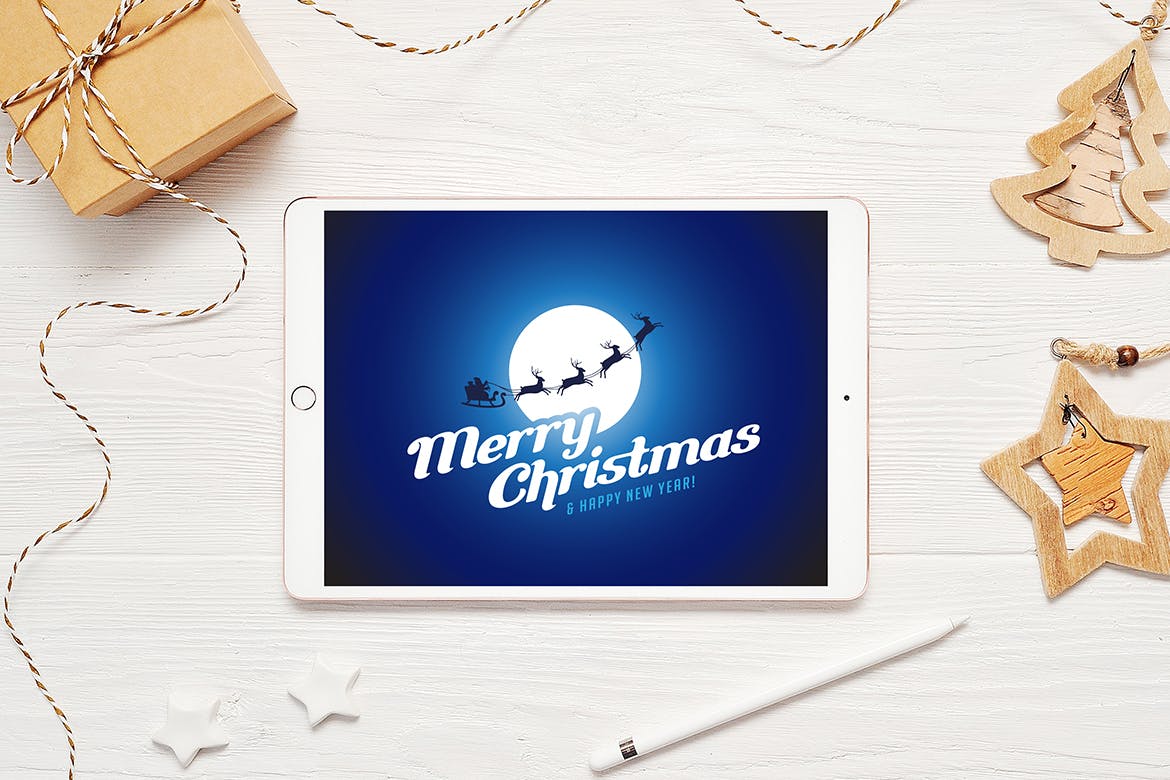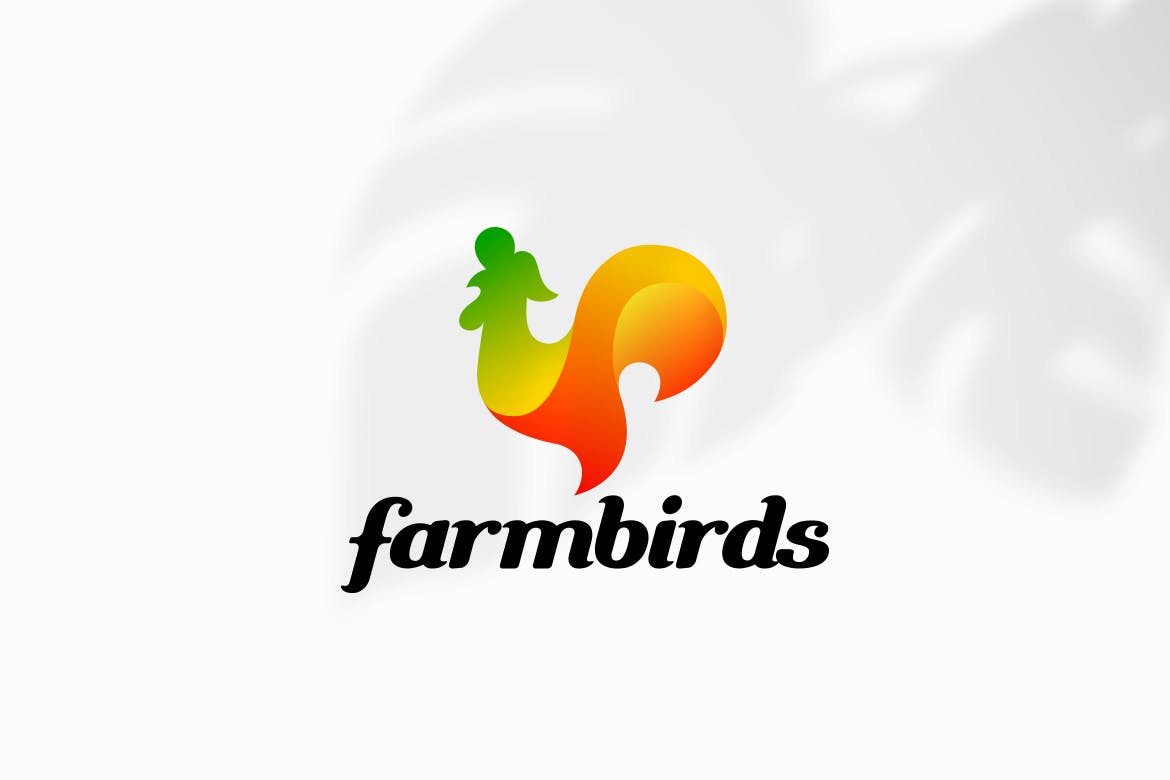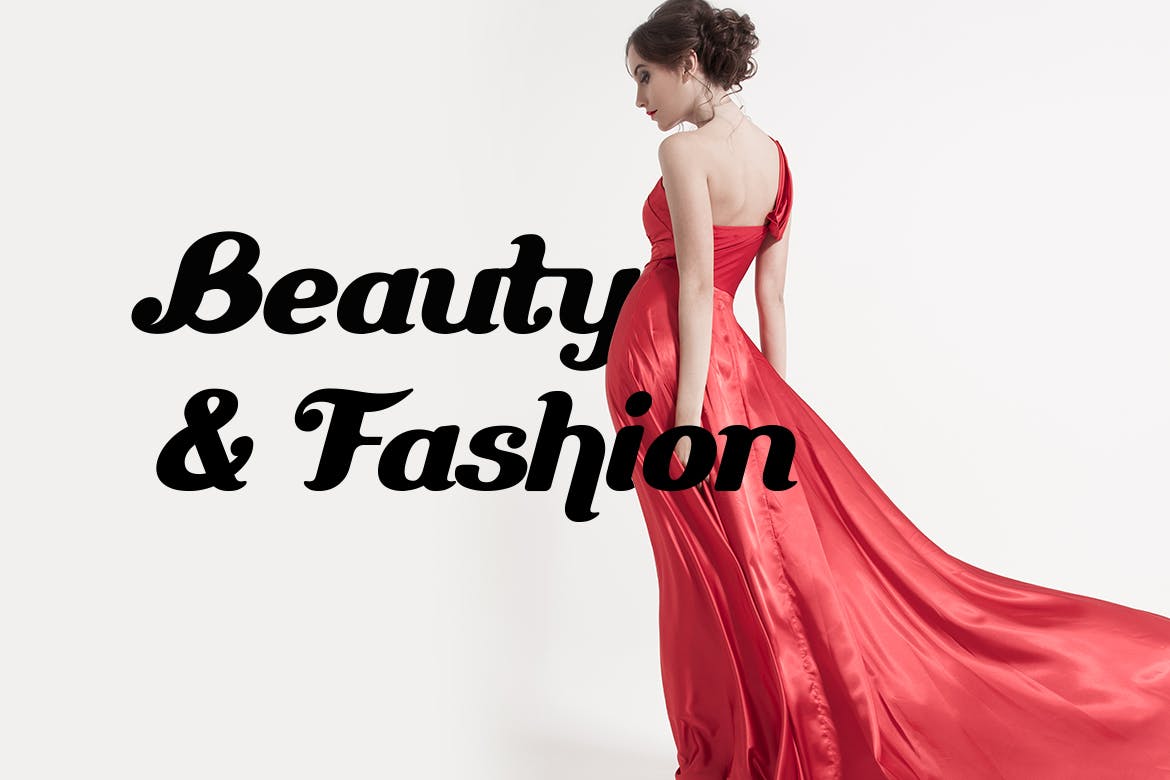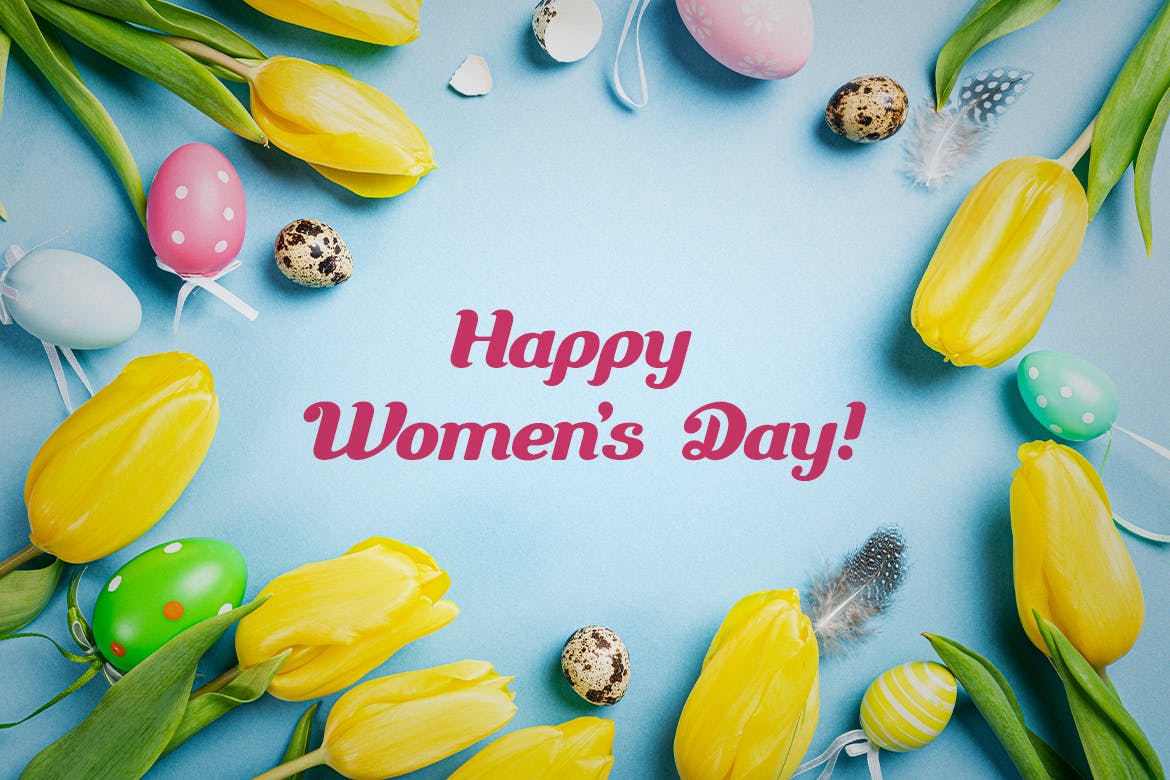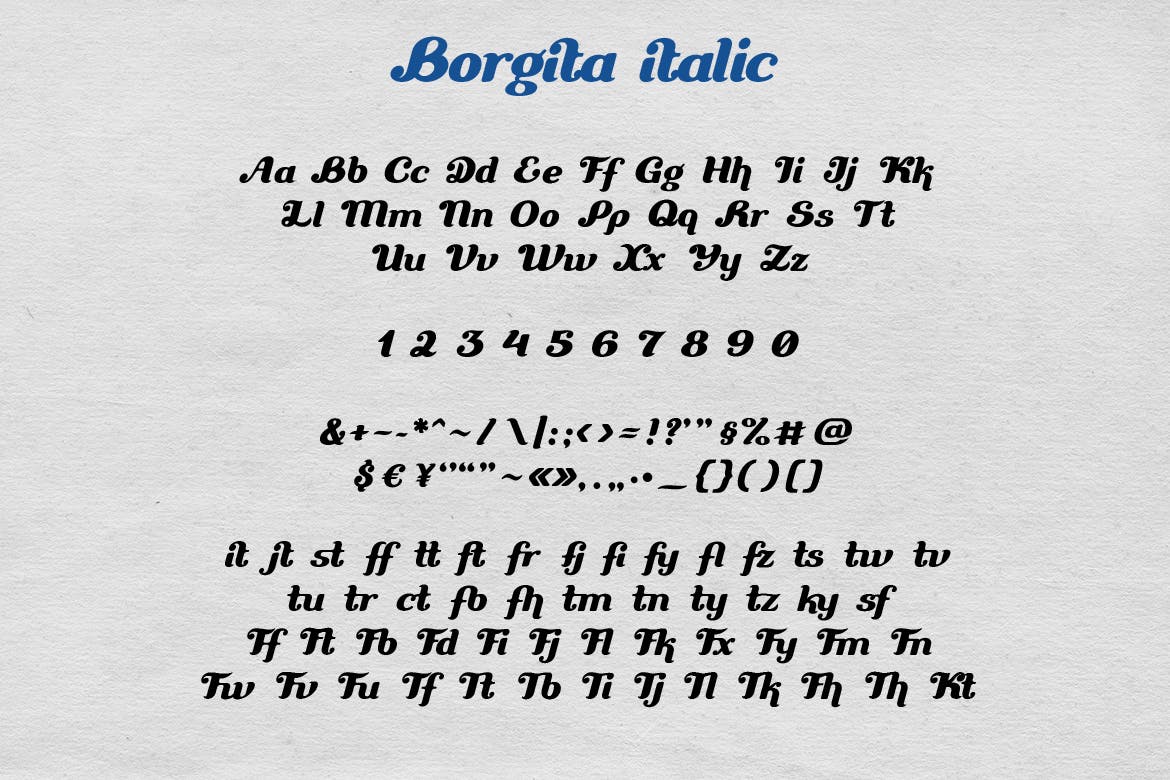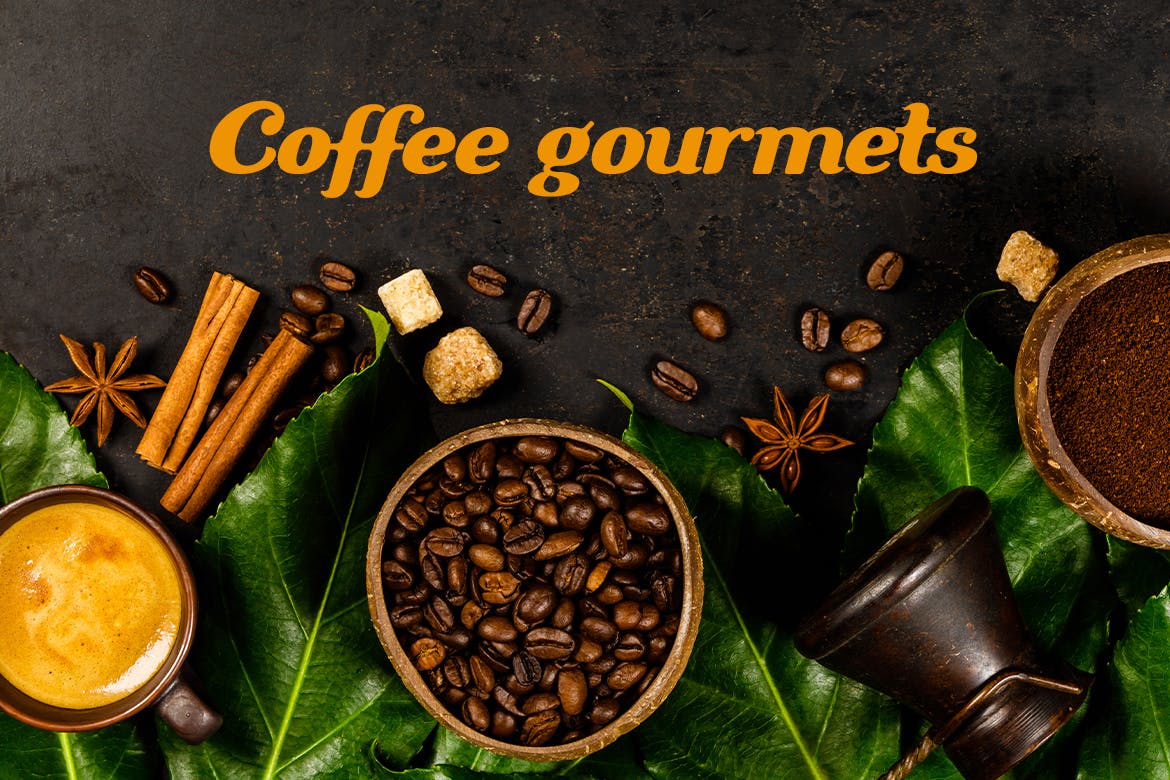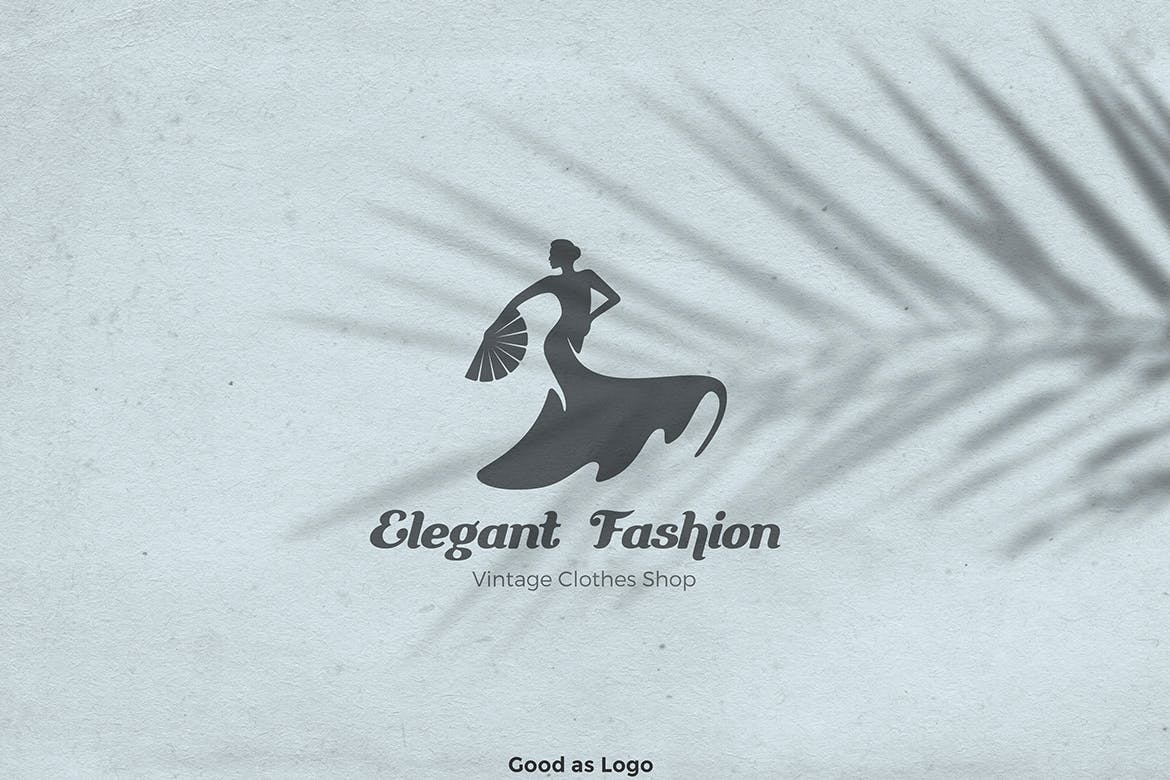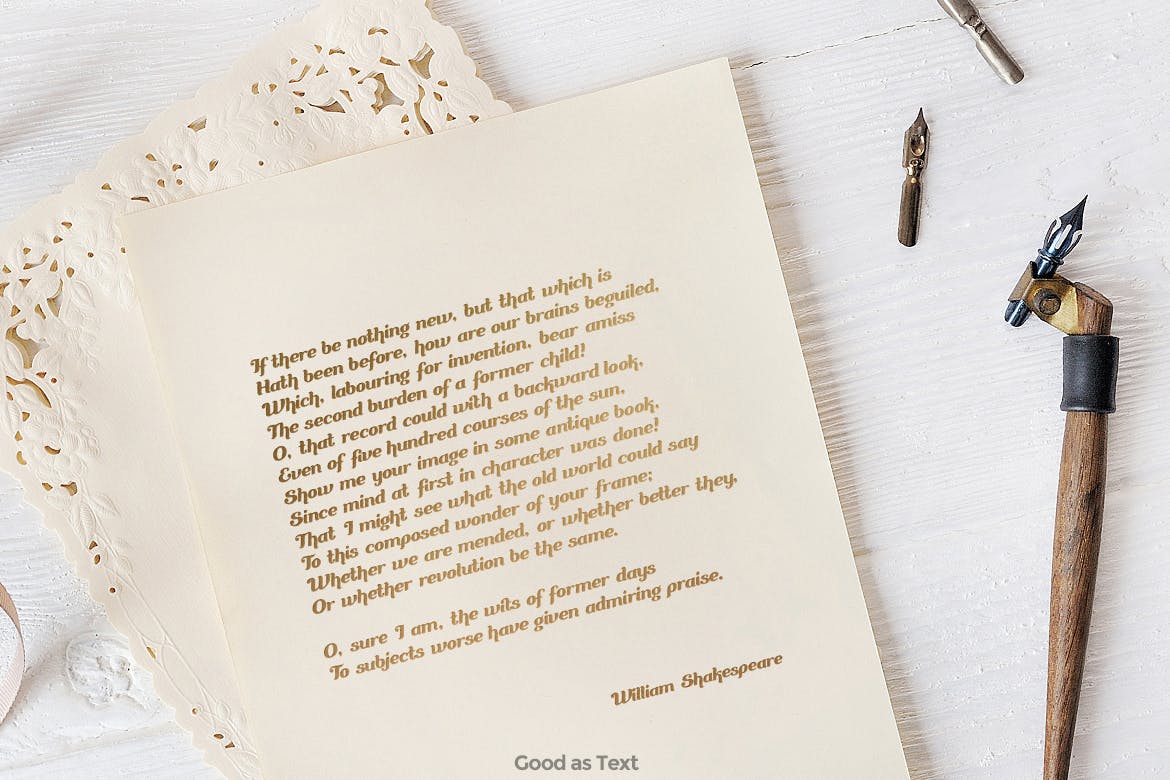
Borgita Italic Script Calligraphic Font
فونت کالیگرافی Borgita Italic مناسب برای طراحی لوگو و ترکیب‌های زیبا.
Borgita یک فونت کالیگرافی ایتالیک است که برای ایجاد لوگوها و ترکیب‌های جذاب و مدرن طراحی شده است.